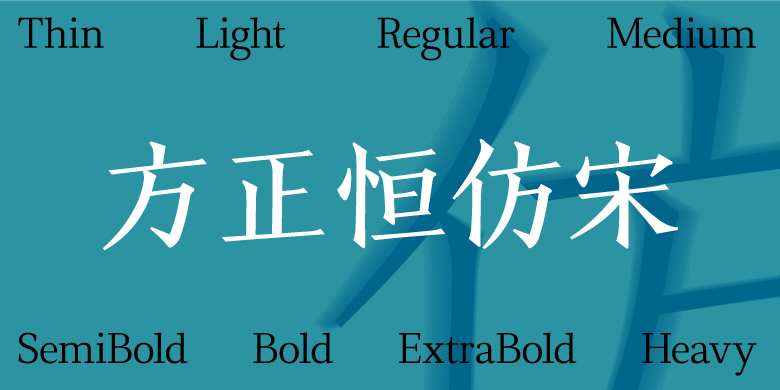
方正恒仿宋家族
方正恒仿宋家族,这款字体结构工整、笔画清晰,兼顾美观与易读性,适用于标题、正文、海报、包装、LOGO 等多种场景。字形优雅稳定,风格百搭耐看,适配日常排版与创意设计,让文字呈现更舒适、更具质感。方正恒仿宋家族一笔一画,皆是细节,以均衡的比例、流畅的线条打造舒适视觉体验,字形端正大气,风格简约现代。无论是商业设计、品牌宣传还是日常排版,都能轻松驾驭,让文字更有格调与力量。方正恒仿宋家族字体下载。
“恒仿宋”打破狭窄修长的规律,布局向上下左右四方伸展拳脚,视觉观感更开扬豁达,把横划略减幼,撇划多少许柔和,而捺划加强劲度,整体劲中带柔,适合高档男女品牌,纤体美容,珠宝首饰,时装品牌,高档房地产宣传,书刊海报等宣传增添新元素,更适合包装设计等,“恒仿宋”是一款商业用途广泛的百搭字体。